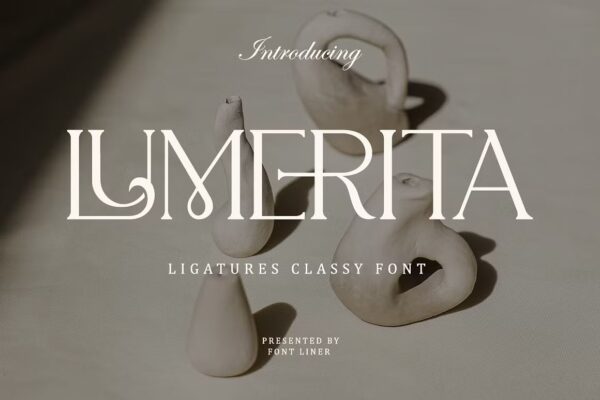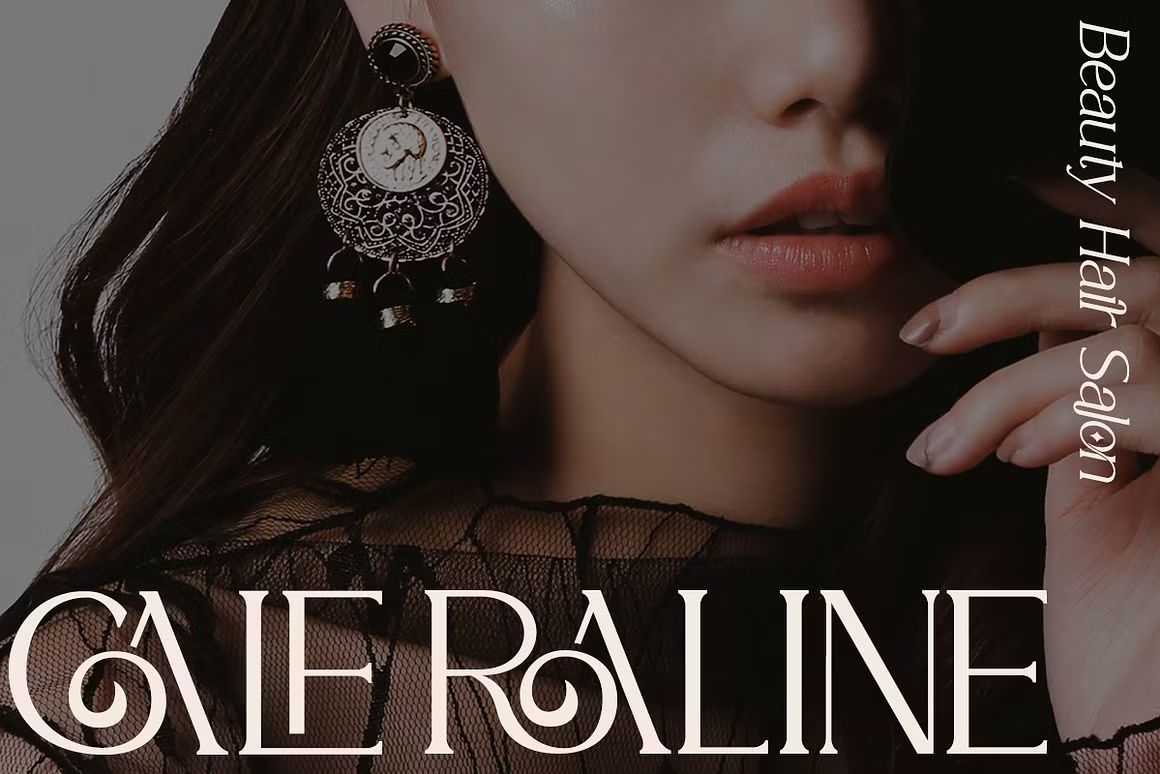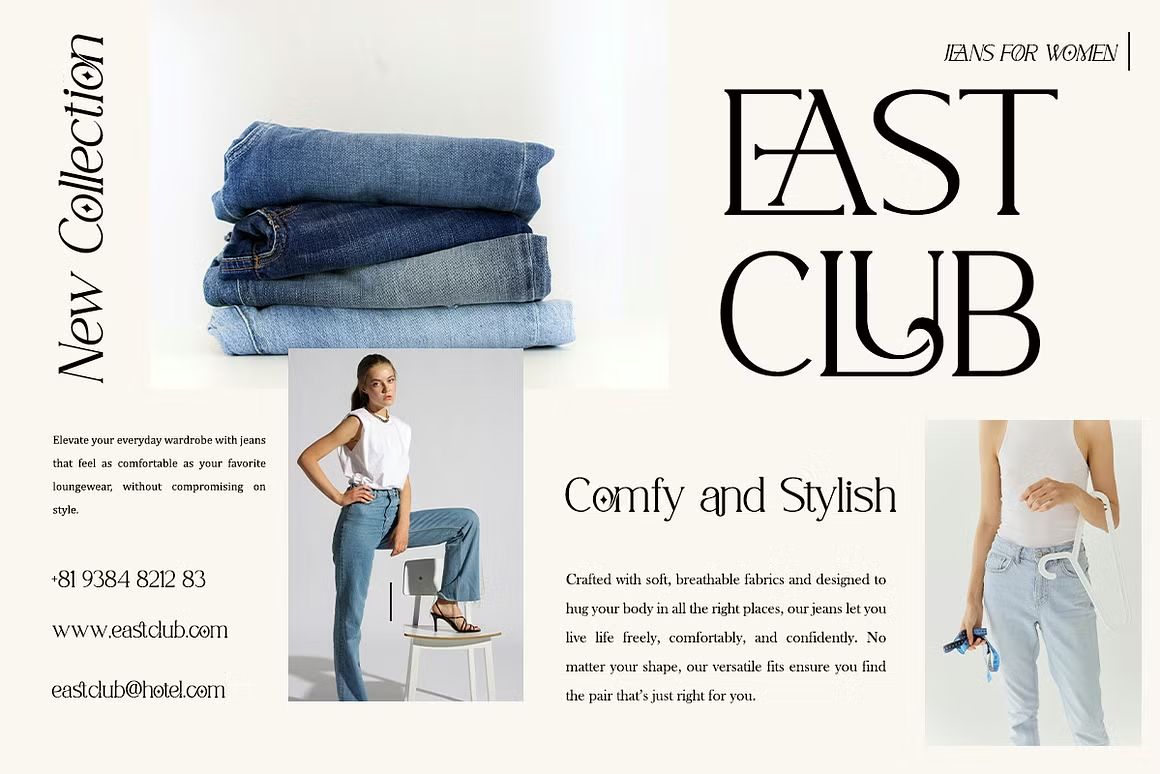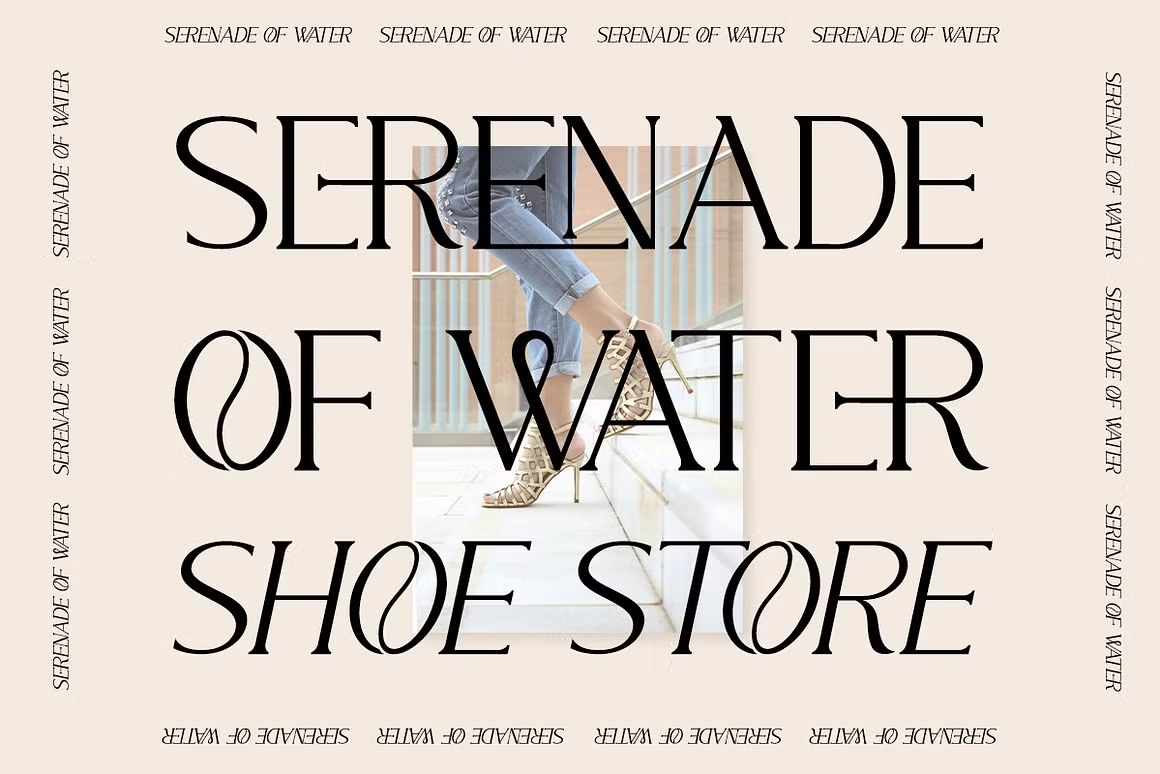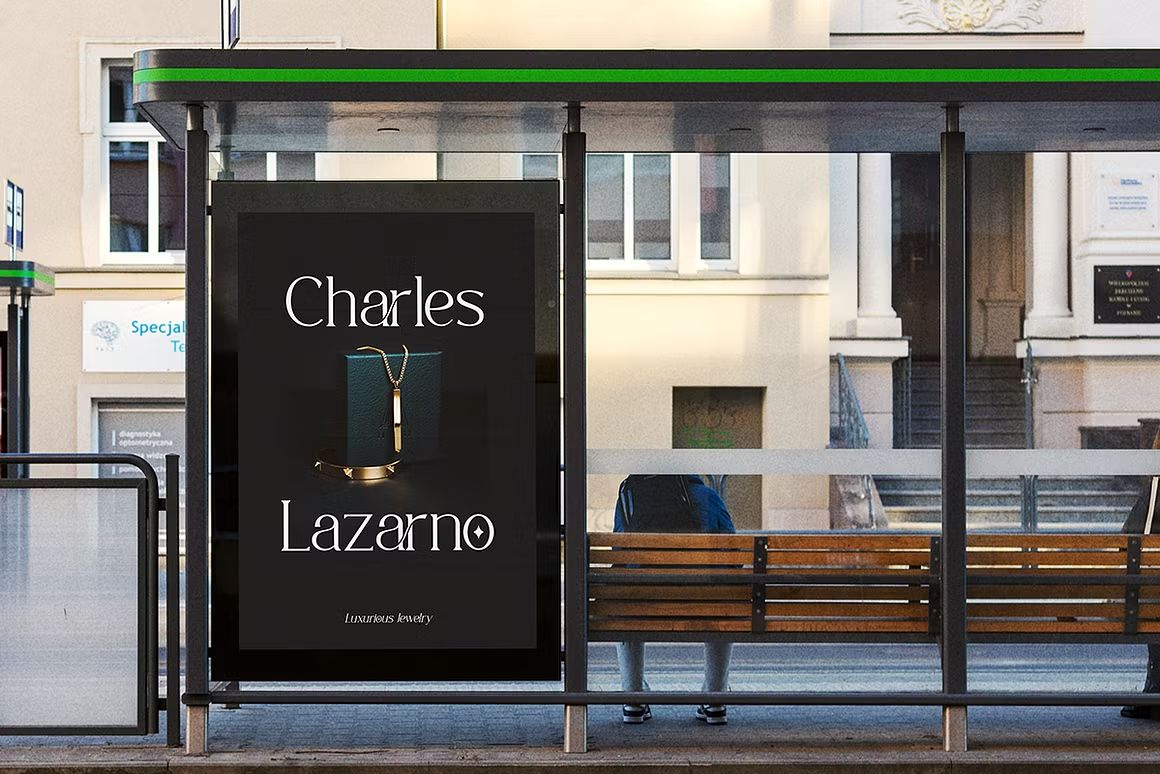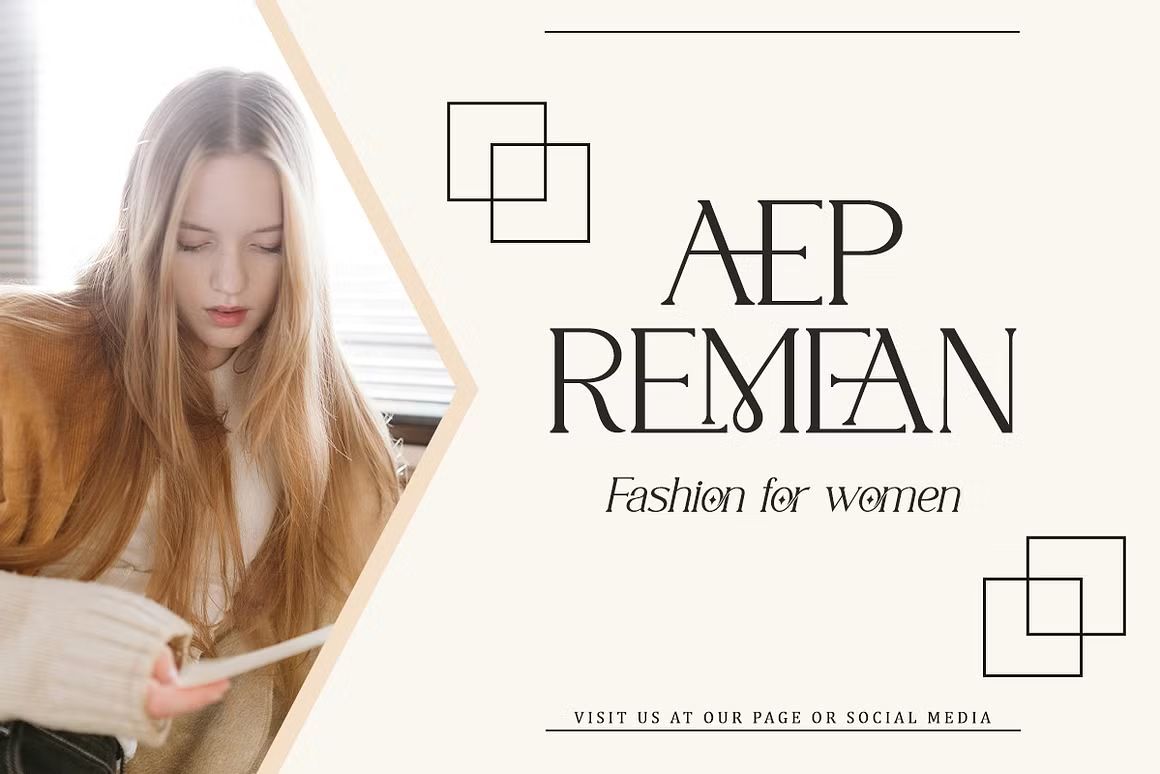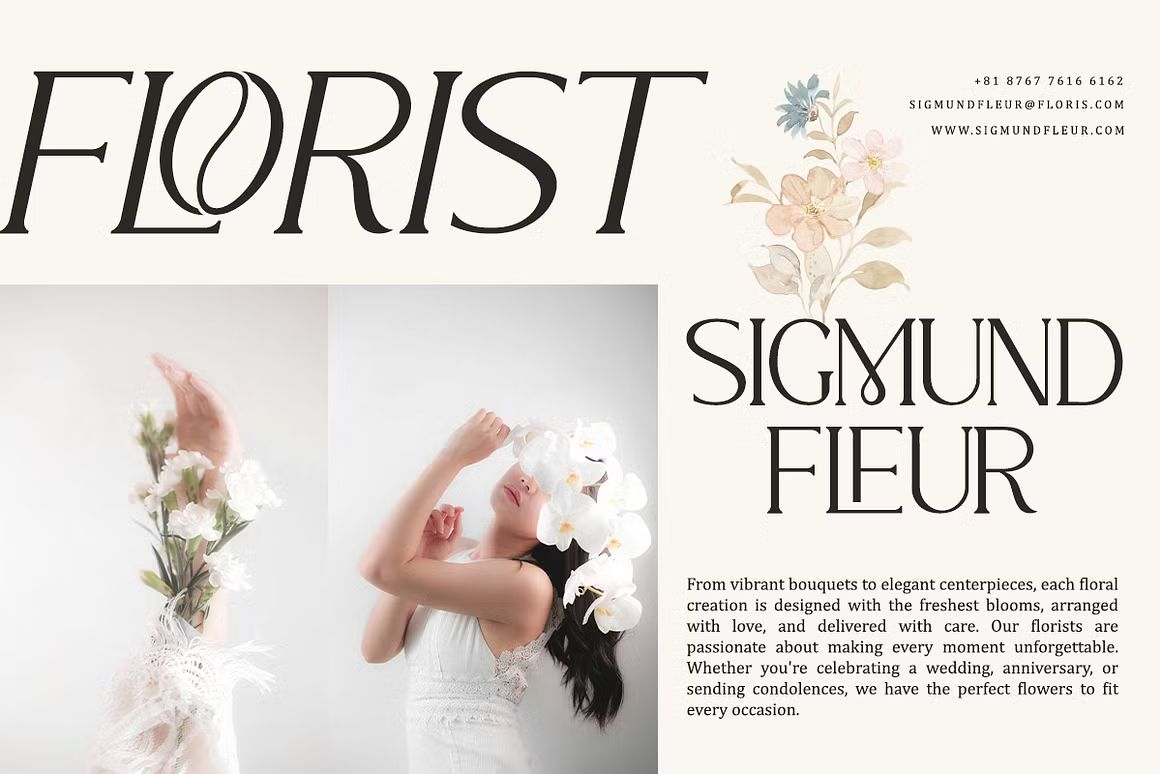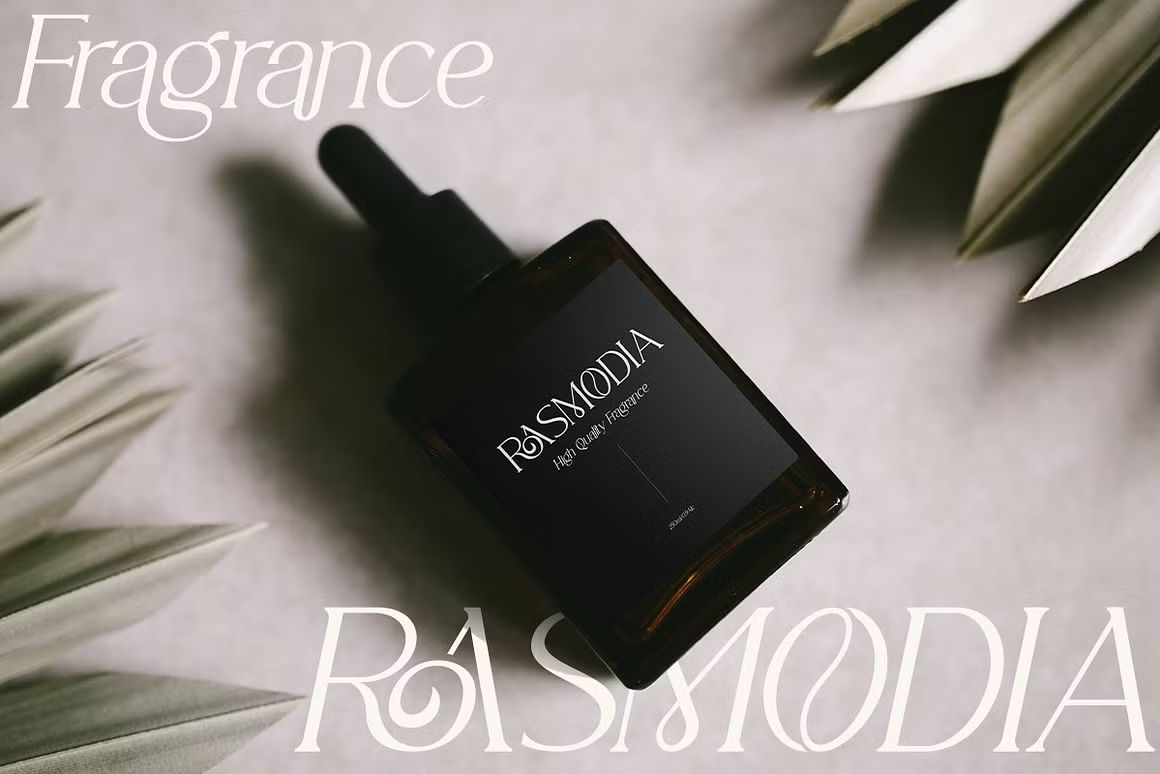
Lumerita – Sans Serif Font
Lumerita adalah font sans serif modern dengan gaya bersih, ramping, dan elegan. Menawarkan bentuk huruf yang seimbang dan mudah dibaca, Lumerita sangat cocok untuk branding, desain editorial, web design, kemasan produk, dan tampilan profesional lainnya. Desainnya yang minimalis memberikan kesan kontemporer yang halus namun kuat.
• Sans serif modern dengan garis halus dan proporsi rapi
• Ideal untuk branding, editorial, dan desain digital
• Termasuk huruf kapital, kecil, angka, dan simbol